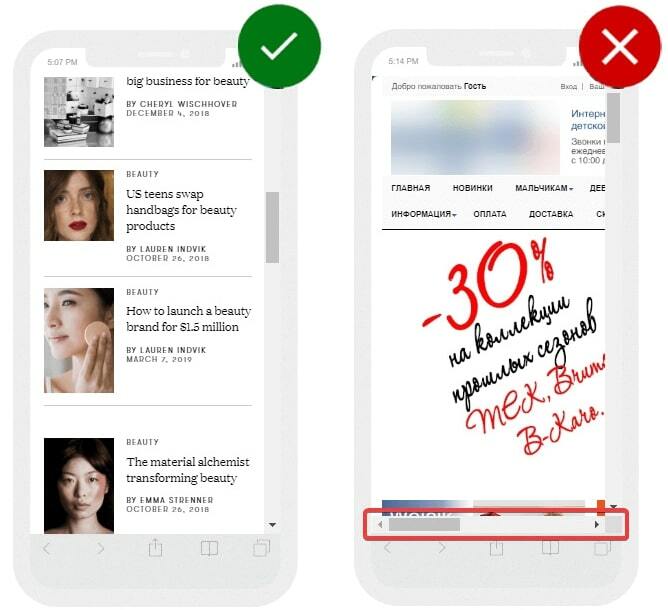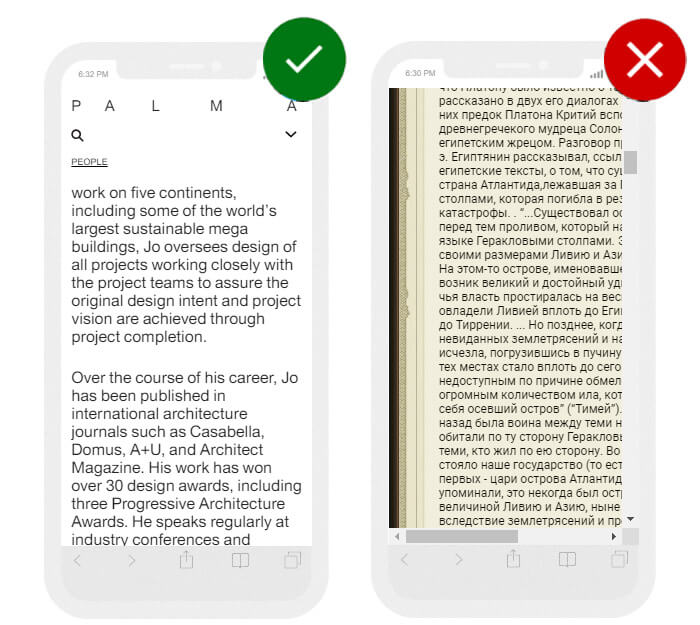
Какими должны быть шрифты, кнопки и цвета в мобильной версии сайта
Как выбрать шрифты для мобильной версии сайта
Для удобства пользователей мобильных устройств необходимо делать ссылки и кнопки на сайте достаточно крупными. Также важно правильно подобрать размер шрифта для мобильного сайта, обращая при этом внимание на межстрочный интервал.
Что такое мобильная типографика
Мобильная типографика — это ответвление искусства оформления печатного текста, посвященное своду правил для максимально удобного восприятия напечатанной информации на портативных устройствах.
В данном примере слева сайт на мобильном устройстве отображается с достаточно разборчивыми шрифтами, вся информация помещается на экране по ширине.
На сайте справа текст слишком мелкий, используется неудачный вариант шрифта для информации об акции. Появляется горизонтальная полоса прокрутки, так как сайт не адаптирован под мобильные устройства:
Мобильная типографика
Горизонтальная полоса прокрутки в мобильной версии
На мобильных устройствах контент должен подаваться таким образом, чтобы обеспечить легкую загрузку, разборчивость и читабельность. При этом не должен страдать функционал, чтобы пользователь мог осуществить все необходимые действия на смартфоне с такой же легкостью, как и на компьютере.
На примере слева все конверсионные кнопки расположены на видном месте, они достаточно крупного размера. На сайте справа слишком мелкие шрифты и не адаптивный дизайн:
Верстка для мобильных устройств
Отсутствие адаптивного дизайна на сайте
Основной принцип мобильного веб-дизайна — предоставлять пользователю необходимый функционал, не перегружая его лишней информацией и призывами к действию. Контент в мобильной версии должен легко поглощаться на бегу, чтобы при необходимости вернуться к нему позже и ознакомиться более детально.
В варианте слева для основного текста используется разборчивый шрифт, длина строки и разделение на абзацы способствуют легкому восприятию материала. Справа текст не разделен на абзацы, шрифт слишком мелкий. Читать подобный контент с мобильного устройства очень сложно:
Адаптация сайта для мобильных устройств
Отсутствие корректного форматирования текста
В мобильном дизайне необходимо обращать внимание на ряд элементов, которые рассмотрим далее.
Рекомендации по веб-типографии для мобильных устройств
Основные рекомендации по веб-типографике касаются следующих моментов:
1. Шрифтов и их размера — они должны быть разборчивыми и соответствовать по стилистике контенту. При этом желательно не смешивать различные шрифты. Важно, чтобы текст был читабельным на любом устройстве.
2. Интерлиньяжа, кернинга и трекинга — оптимального интервала между строчками, определенными парами букв и групп символов.
3. Пустого пространства — помимо расстояния между строками, важно наличие отступов и абзацев, облегчающих восприятие текста.
4. Длины строки — приемлемого количества символов в одной строке.
5. Иерархии — сочетания заголовков и основного текста.
6. Выравнивания — выбора правильного варианта из 4 возможных: по левому или правому краю, по центру либо по ширине.
7. Контраста — подбора достаточно мягких сочетаний, ослабляющих контраст.
Более подробно об этом и других нюансах веб-типографики для мобильных устройств поговорим в следующем разделе.
Какой размер шрифта использовать на сайте
Рекомендации отличаются в зависимости от используемой операционной системы, однако в любом случае размер букв должен быть удобным для чтения:
Размер шрифта для мобильных устройств
Оптимальный размер шрифтов для мобильных устройств
Так как у всех разные устройства, уровень зрения, и условия просмотра, то стоит учесть, что единого идеального варианта вам все равно не удастся сделать. Поэтому нужна золотая середина, которую можно определить с помощью тестирования. Попросите коллег или пользователей посмотреть сайт на своем устройстве и дать обратную связь.
Также в зависимости от тематики сайта, стоит разобраться в каких условиях люди читают размещенные статьи, например, в общественном транспорте или пешком на работу. Это можно проследить в той же аналитике (просмотр времени посещения). Если основной трафик утром и вечером, значит, люди читают по дороге на работу и обратно.
Более подробные инструкции можно получать, используя информацию, размещенную на Material Design.
Размер заголовков
Важно правильно подобрать размеры для всех уровней заголовков, используемых в тексте, чтобы подчеркнуть иерархию. Если для основного текста используется размер 16 px, для заголовков можно применять такие параметры:
• 42 px — для основного заголовка H1;
• 36 px — для заголовков второго уровня;
• 30 px — для H3;
• 24 px — для H4;
• 20 px — для H5;